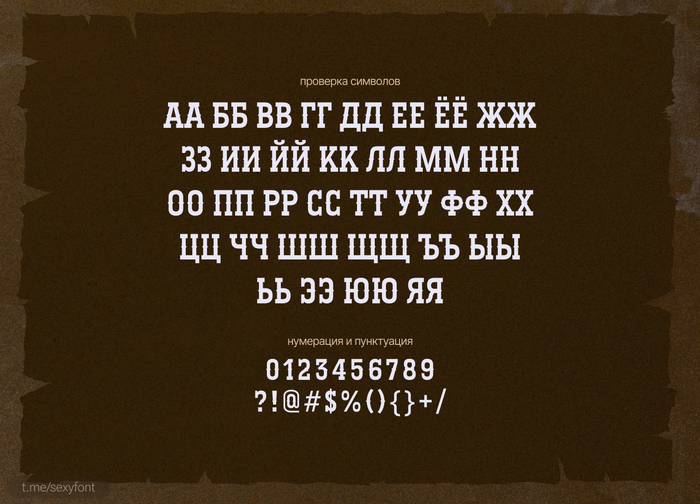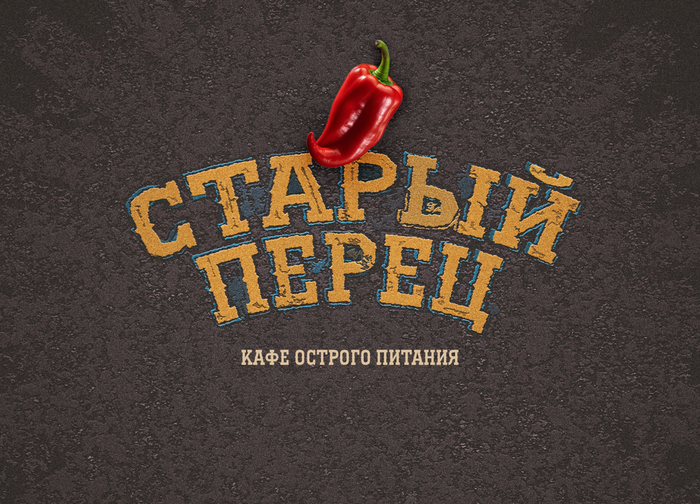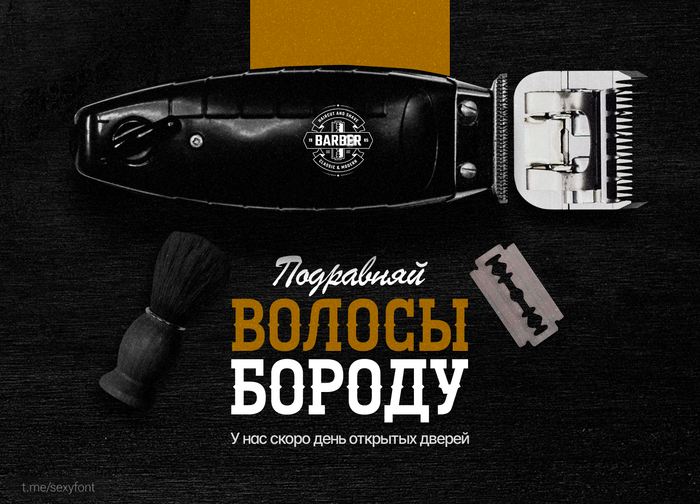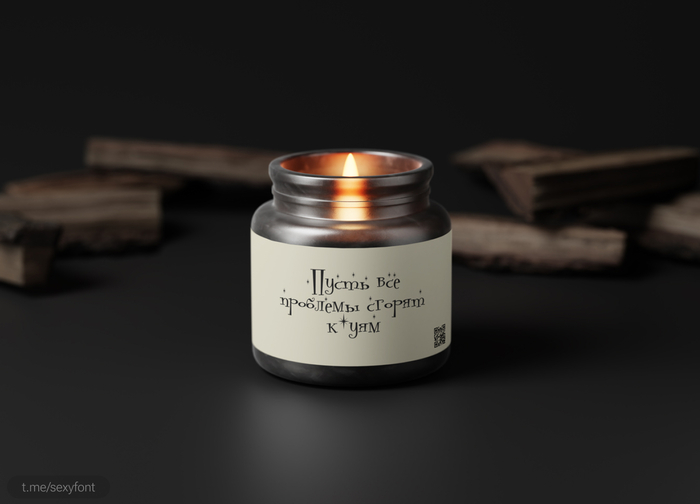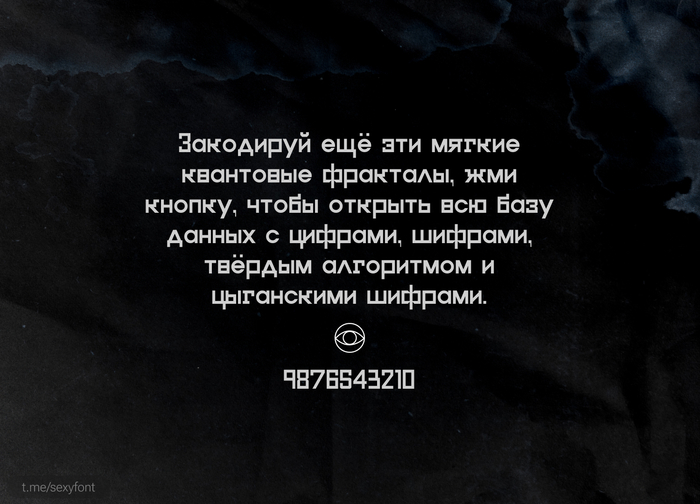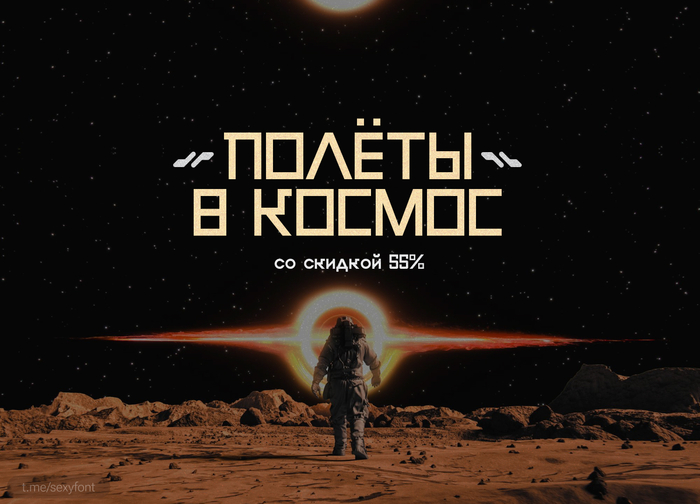
Готический шрифт с кириллицей
Сегодня делал презентацию на мистическую тему для нашего канала с исходниками. Использовал там готический шрифт Deutsch Gothic. Мне стало интересно, что еще есть на эту тему. И нашел lombardina initial
Забираем готический шрифтец. Да, читаемость не айс, но зато как эффектно сделаны заглавные буквы!)
Шрифт Serpantin
🏖 Шрифт с нотками лухари) Допилил новую презентацию
Serpantin — элегантный шрифт с ретро-оттенком, вдохновленный стилем ар-деко.
Автор: Alexandra Gophmann
Vertiger. Это сжатый, грубый и ритмично повторяющийся шрифт, который передаёт загадочное очарование мистических кинопостеров 1950-х и 1960-х годов.Автор: Ilya Designgsta
Шрифт Экран
Шрифт Экран. Компактный и вместительный шрифт. Таких не так много) В меру читаемый, но использовать лучше в крупных заголовках. «Экран» черпает вдохновение из заголовочных шрифтов, использовавшихся в македонском еженедельном журнале «Экран» 1970-х годов.
Автор: Nebojsa (Bane) Gelevski
Бесплатный шрифт Raznochin
Идеально для ковбойских тематик бесплатный шрифт от Василия Шишкина.
Так же отлично впишется под кафешки. Читается только в коротких заголовках.Бесплатно для личного и коммерции
Шрифт Pudelinka
Pudelinka. Шрифт с очень милым названием. Буквы содержат звёздочки. Идеально под зимние, новогодние тематики. В меру читаемый в заголовках и коротких текстах) Для детских, сказочных тем тож вполне подойдет.
Автор кириллизации: Gophmann A.L
Новая презентация готова) Шрифт Galiver sans
Привет. Доделал еще одну презентация шрифта. Остроугольный, слегка футуристичный шрифт. Особенно цифры и буква «ф» Единственное, что смущает меня это строчная буква «к»
Автор: FontCreator 9.0
Семейство Bodoni
Внезапно, в процессе работы выяснилось, что нет сабжевого кирилического шрифта. Но Бодони не простой, а конденсед, т.е. чутка сплющенный, ну вы поняли. Прошу камрадов поделиться сокровищем на какое-нибудь «облако». Пиво телеграфирую. Спасибо.
Семейство Bodoni